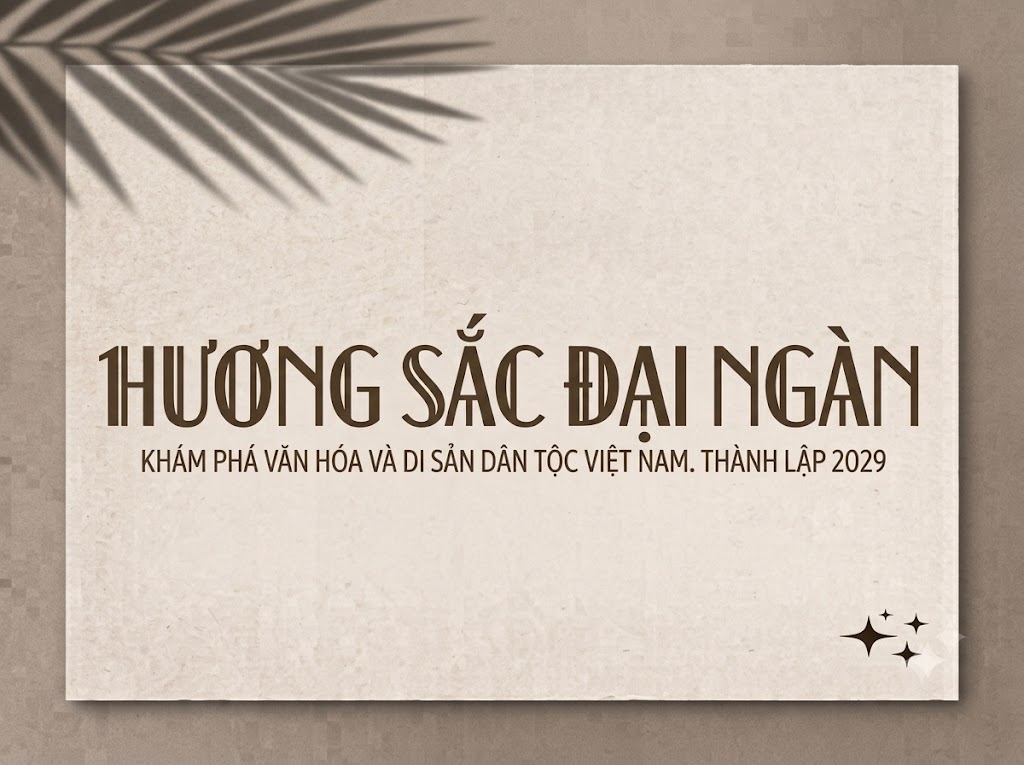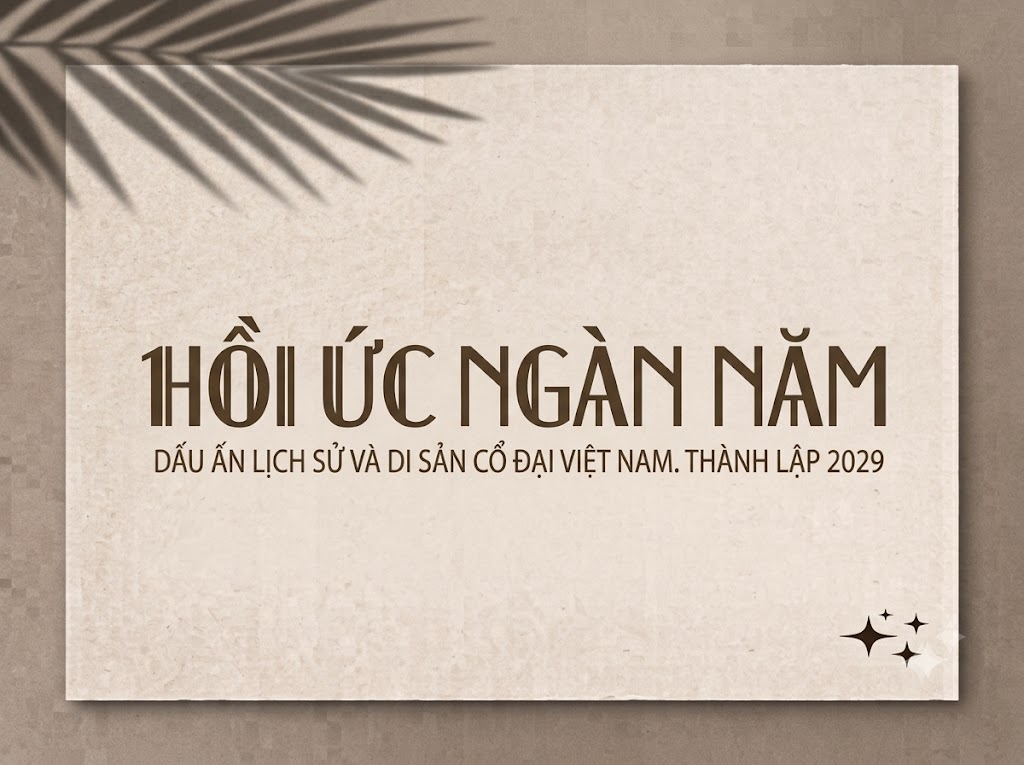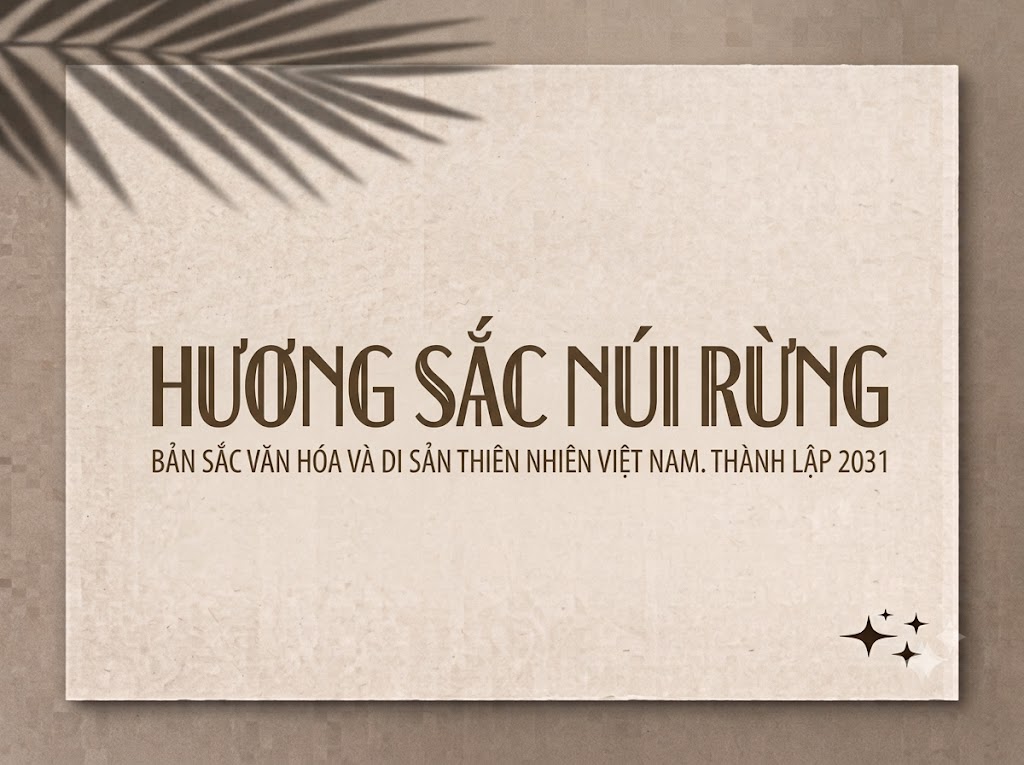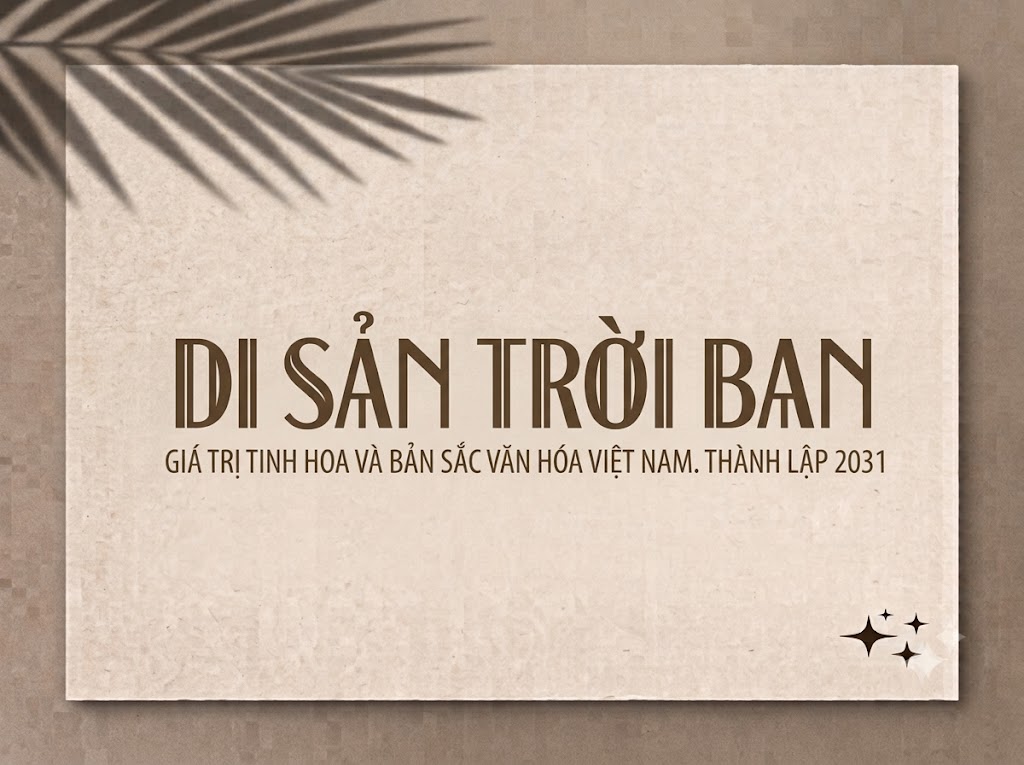
1FTV Dexurita
Trong các dự án thiết kế cao cấp đòi hỏi tính nghệ thuật và chiều sâu, việc lựa chọn một phông chữ tiêu đề thể hiện được sự đẳng cấp, quý phái luôn là bài toán được các nhà sáng tạo đặc biệt quan tâm.
Một font chữ quá đơn điệu hoặc mang tính công nghiệp đại trà sẽ khó lòng truyền tải trọn vẹn nét tinh tế, xa xỉ của các thương hiệu thời trang, mỹ phẩm hay các ấn phẩm truyền thông nghệ thuật.
Nếu bạn đang tìm kiếm một giải pháp typographic mang hơi hướng cổ điển, độc đáo và đầy kiêu sa để nâng tầm các dòng tiêu đề của mình, thì font 1FTV Dexurita chính là câu trả lời lý tưởng.
Giới thiệu về font 1FTV Dexurita
Font 1FTV Dexurita là một bộ chữ hiển thị (display font) sở hữu phong cách thiết kế giao thoa tinh tế giữa nét hoài cổ cổ điển và cấu trúc hình học hiện đại.
Bộ phông chữ này được tối ưu hóa hoàn chỉnh ở phiên bản Version 1.000, đem lại kết cấu đường nét vô cùng mượt mà và độ ổn định cao khi sắp xếp bố cục văn bản.
Sản phẩm xuất hiện trong bài viết sở hữu định dạng OpenType Layout cao cấp, đi kèm chứng thực kỹ thuật số (Digitally Signed) và hệ thống nét chữ dạng PostScript Outlines siêu chuẩn.
Nhờ những thông số kỹ thuật tối ưu này, phông chữ đảm bảo khả năng hiển thị vô cùng sắc nét trên các màn hình độ phân giải cao, giúp bạn tự tin ứng dụng trên mọi phần mềm đồ họa chuyên nghiệp mà không lo lỗi vỡ nét hay răng cưa khi phóng lớn.
Đặc điểm nổi bật của phong cách thiết kế Dexurita
Sức hút lớn nhất của font 1FTV Dexurita đến từ phom dáng đứng cao ráo kết hợp cùng những nét vát nhọn nhẹ nhàng (flair serif) đầy nghệ thuật ở các đầu ký tự.
Phông chữ được xây dựng theo định dạng All-Caps (thiết kế viết hoa đồng bộ cho cả hai hàng ký tự chữ hoa và chữ thường trên hệ thống), mang lại sự cân bằng tuyệt đối về mặt cao độ và tạo ra các khối chữ vô cùng chắc chắn, bắt mắt.
Điểm nhấn đắt giá của Dexurita nằm ở sự nhấn nhả lực nét thanh đậm tinh tế cùng cách tạo hình đầy ngẫu hứng trên các ký tự như chữ R, K, E, F với phần thanh ngang được đặt phá cách. Cấu trúc độc đáo này gợi liên tưởng mạnh mẽ đến trường phái kiến trúc và mỹ thuật Art Deco đầy xa xỉ, lãng mạn của thế kỷ trước.
Để phông chữ vận hành mượt mà trên mọi hệ điều hành từ Windows đến macOS, phiên bản font 1FTV Dexurita đã trải qua quy trình xử lý thông số kỹ thuật vô cùng nghiêm ngặt.
Hệ thống khoảng cách chữ (kerning) và độ giãn dòng đã được căn chỉnh chuẩn xác, giúp các khối chữ khi đứng cạnh nhau luôn giữ được khoảng trống thẩm mỹ lý tưởng, không bị dính nét hay gây cảm giác rối mắt cho người xem.
Bên cạnh hệ thống chữ cái viết hoa đồng bộ, font còn tích hợp đầy đủ dãy số từ 0-9 dáng đứng thanh thoát cùng hệ thống các ký tự đặc biệt, dấu câu thông dụng (1234567890.:,;'"(!?)+-*/=).
Bản Việt hóa chuẩn chỉnh này giúp các nhà sáng tạo nội dung hoàn toàn yên tâm thiết kế các văn bản tiếng Việt có dấu mà không lo gặp phải tình trạng nhảy font hay lỗi hiển thị ký tự.
Hình ảnh demo thực tế của font 1FTV Dexurita
Để giúp bạn dễ dàng hình dung khả năng co giãn và hiển thị linh hoạt của phông chữ này trên các kích thước khác nhau, hãy cùng xem qua bảng mô phỏng từ file hệ thống image_43e524.png:
Kích thước nhỏ (12pt – 24pt): Nhờ cấu trúc chữ đứng cao và khoảng hở chữ thông thoáng, các nét chữ thanh mảnh vẫn hiển thị rõ ràng, ngay ngắn và dễ đọc trên giao diện màn hình di động.
Kích thước lớn (36pt – 72pt): Đây là đất diễn hoàn hảo nhất để font chữ phô diễn toàn bộ sự kiêu sa, quý phái, tạo tác động thị giác mạnh mẽ chiếm trọn tâm trí người xem cho các dòng headline chính.
Ứng dụng của font Dexurita trong thiết kế đồ họa và làm video
Sở hữu nét cá tính sang trọng, hoài cổ và cấu trúc hình khối đậm chất nghệ thuật, font 1FTV Dexurita mở ra không gian sáng tạo vô cùng rộng lớn cho các dự án truyền thông hiện đại:
Làm tiêu đề cho video ngắn (TikTok, Reels, Shorts): Dáng chữ đứng cao ráo và bắt mắt này cực kỳ hoàn hảo để làm các cụm tiêu đề chính giật tít ở phần mở đầu video. Độ cuốn hút của chữ giúp giữ chân người xem lướt feed dừng lại ngay lập tức, đồng thời hiển thị vô cùng nổi bật trên các khung hình dọc 9:16 của thiết bị di động.
Thiết kế ảnh thu nhỏ YouTube (Thumbnail): Đây là lựa chọn tuyệt vời cho các thumbnail thuộc chủ đề phong cách sống, chia sẻ kiến thức, review phim ảnh hoặc nội dung nghệ thuật nhờ độ hiển thị trực diện, dễ nhìn từ khoảng cách xa.
Banner và Poster quảng cáo e-commerce cao cấp: Hoàn hảo cho các poster giới thiệu sản phẩm thời trang, mỹ phẩm, trang sức xa xỉ, hoặc các chiến dịch marketing kỹ thuật số đòi hỏi sự tinh tế, súc tích nhưng vẫn giữ được vẻ quý phái.
Nhận diện thương hiệu phong cách Luxury: Phù hợp làm logo dạng chữ khối, biểu ngữ quảng cáo, menu nhà hàng cao cấp, thiệp mời sự kiện VIP hoặc thiết kế nhãn mác cho các thương hiệu local brand thời trang, tiệm cà phê hoặc studio sáng tạo hướng tới vẻ đẹp thanh lịch, bền vững.